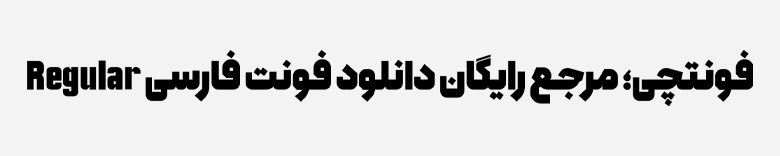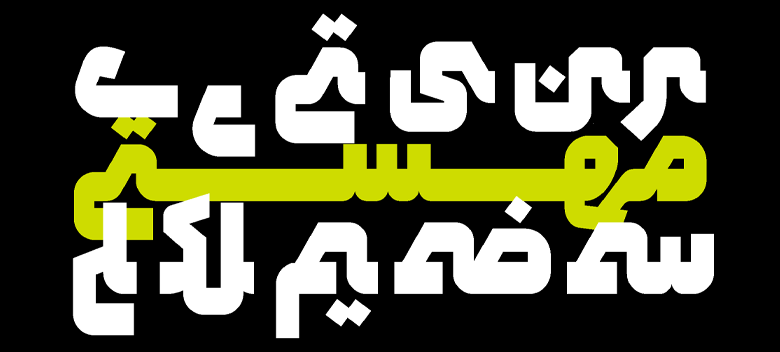
فونت همراه (Hamrah)
فونت همراه (Hamrah) الهام گرفته از فونت کوفی بنایی است که با هندسه خاصی که در شکستگیها، منحنیها و چشمی حروف دارد، ظاهری کاملا استخوانی و سنگین به این فونت داده که آن را به گزینه ایدهآل برای فونت عناوین و محتواهای تبلیغاتی تبدیل کرده است.
این فونت که توسط وحید یعقوبلو طراحی شده، دارای شخصیتی جدی است که خطوط در حروف کاملا مستقیم هستند، اما منحنیها ظاهری صمیمی به این فونت داده است. چشمیها در این فونت از حد استاندارد کوچکتر در نظر گرفته شده تا هماهنگی بیشتری را برای به کرسی نشستن حروف ایجاد کند. توسعه این فونت توسط امین عابدی صورت پذیرفته است.
در ادامه این نوشته از سایت فونتچی به نقد و بررسی این فونت هندسی خواهیم پرداخت که با دانلود فونت همراه میتوانید از آن در موضوعات مختلفی همچون عناوین در تیتر روزنامه و مجلات، صنایع بستهبندی، لوگوتایپ و هر جایی که احساس میکنید استفاده از یک فونت با وزن سنگین زیبایی خاصی بهدنبال دارد استفاده کنید.
معرفی و بررسی فونت همراه (Hamrah)
در طراحی فونت همراه از یک ساختار کاملا یکسان با گرید بندی ثابت استفاده شده است. حروف و خطوط در این فونت تقریبا پهنای بسیار نزدیک بههم دارند که همین مسئله آن را در عین هندسی بودن و مناسب برای فونتهای عناوین، به یک فونت با کنتراست بالا تبدیل کرده است.
میتوان از این فونت در انواع محیطهای فیزیکی برای چاپ بنر و بیلبوردهای تبلیغاتی استفاده کرد تا کلمات و متونی که نیاز به تاکید و دیده شدن بیشتر دارند، مورد توجه قرار گیرد. در فضای دیجیتال نیز میتوان از این فونت برای طراحی انواع بنر، اسلایدر و پست در شبکههای اجتماعی استفاده کرد.
یکی دیگر از ویژگیهای این فونت مناسب بودن برای تیتر و عناوین است که با توجه به پشتیبانی از فرمت مناسبی که مختص آن دارد میتوان برای وب فونت از آن استفاده کرد که در ادامه مفصل به معرفی این قابلیت فونت hamrah خواهیم پرداخت.
وزن و سبک فونت همراه
سبک فونت همراه ضخیم و کاملا جدی است؛ کاربرد آن در فونت عنوان و مناسب تبلیغات درنظر گرفته شده است. از همینرو صرفا از یک وزن معمولی Regular پشتیبانی میکند که اگر در نگاه اول وزن این فونت را ببینید، تصور خواهید کرد که وزن سیاه یا سنگین آن را مشاهده میکنید.
این فونت با اصالت پهنای زیادی در سرتاسر حروف و سطح مقطعهای پایین و بالای حروف دارد و از نقطهگذاری و چشمیهایی کاملا تیز پشتیبانی میکند که بخش صمیمی این فونت صرفا منحنی های حروف هستند.
ویژگی و مشخصات فونت Hamrah
پیش از دانلود فونت همراه بد نیست نگاهی به ساختار و ویژگیهایی که این فونت عنوان و هندسی دارد داشته باشیم.
پشتیبانی از زبان انگلیسی و عربی
فونت همراه فارسی از زبانهای انگلیسی و عربی نیز پشتیبانی میکند. پشتیبانی از زبان عربی در قالب همان نسخه فارسی است که اعراب و حروف عربی را نیز در خود جای داده است. انواع اعراب از فتحه و کسره گرفته، تا ضمه و تنوینها در این فونت جایگرفته است.
برای زبان انگلیسی نیز طراحی بهخصوصی در نظر گرفته نشده و از یک وزن سنگین فونتهای رایج انگلیسی استفاده شده است که به طور دقیق با توجه به تنوعی که فونتهای انگلیسی دارند، نمی توان حدس زد که کدام فونت انگلیسی است.
ترکیبات و کاراکترهای خاص نیز در هر سه زبان در این فونت پیادهسازی شده تا آن وزن سنگین و پهن را در عین اینکه فونت دارای وزن معمولی است در خود جای دهد.
پشتیبانی از حروف و ترکیبات جایگزین
در این فونت هم مشابه با سایر فونتهای مناسب عناوین و تبلیغات امکان استفاده از حروف جایگزین و ترکیبات خاص فراهم شده تا بتوانید برخی حروف را در کلمات دلخواه با ظاهری متفاوت تایپ کنید. این ظاهر متفاوت در عینحال که ممکن است نشان از بینظمی داشته باشد، ساختاری زیبا به فونت داده و با توجه به برهم خوردن نظم فونت، موجب توجه بیشتر میشود که در مبحث تبلیغات تاثیر روانی خوبی روی توجه کاربران خواهد داشت.
حروفی همچون «ه، ی، ر» و برخی حروف دیگر در این فونت از این ساختار قابل تغییر پشتیبانی میکنند که میتوانید از ابتدا تا انتهای کلمات از این جایگزینها بسته به نوع حروف الفبای فارسی یا عربی استفاده کنید.
جدا از این حروف جایگزین یکسری ترکیبات هم هستند که در زبان فارسی و عربی بسیار مورد استفاده قرار میگیرند، ترکیباتی که به مواردی مثل «ـر، ـی، ـهـ» که در فونت همراه قابل تایپ به چند شکل مختلف هستند و میتوان از آنها در چند بخش مختلف محتوا استفاده نمود.
پشتیبانی از اعداد هک شده فارسی و عربی
این فونت ضمن پشتیبانی از اعراب و کاراکترهای خاص برای هر زبان، دارای نسخه مناسب برای پشتیبانی از اعداد در هر زبان است. در صورتی که نسخههای FD را استفاده کنید، اعداد فارسی بهصورت هک شده در این فونت جای گرفته است. در این صورت ضمن اینکه صفحه کلید شما انگلیسی است، میتوانید اعداد را با هک فارسی یا عربی مشاهده کنید.
اعداد عربی «۴، ۵ و ۶» همانطور که در تصویر زیر هم میبینید ظاهر متفاوتی دارند که در صورت تایپ به این صورت نمایش داده خواهند شد. اما اگر صفحه کلیدی روی فارسی استاندارد قرار داشته باشد با همان ترکیب فارسی تاپ میشوند.
نسخه انگلیسی هم از اعداد مختص خود پشتیبانی میکند. یکی از مزیتهای پشتیبانی این فونت از اعداد بر اساس زبان و هک شده فارسی اسن است که در سایت بسیار مورد توجه قرار میگیرد.